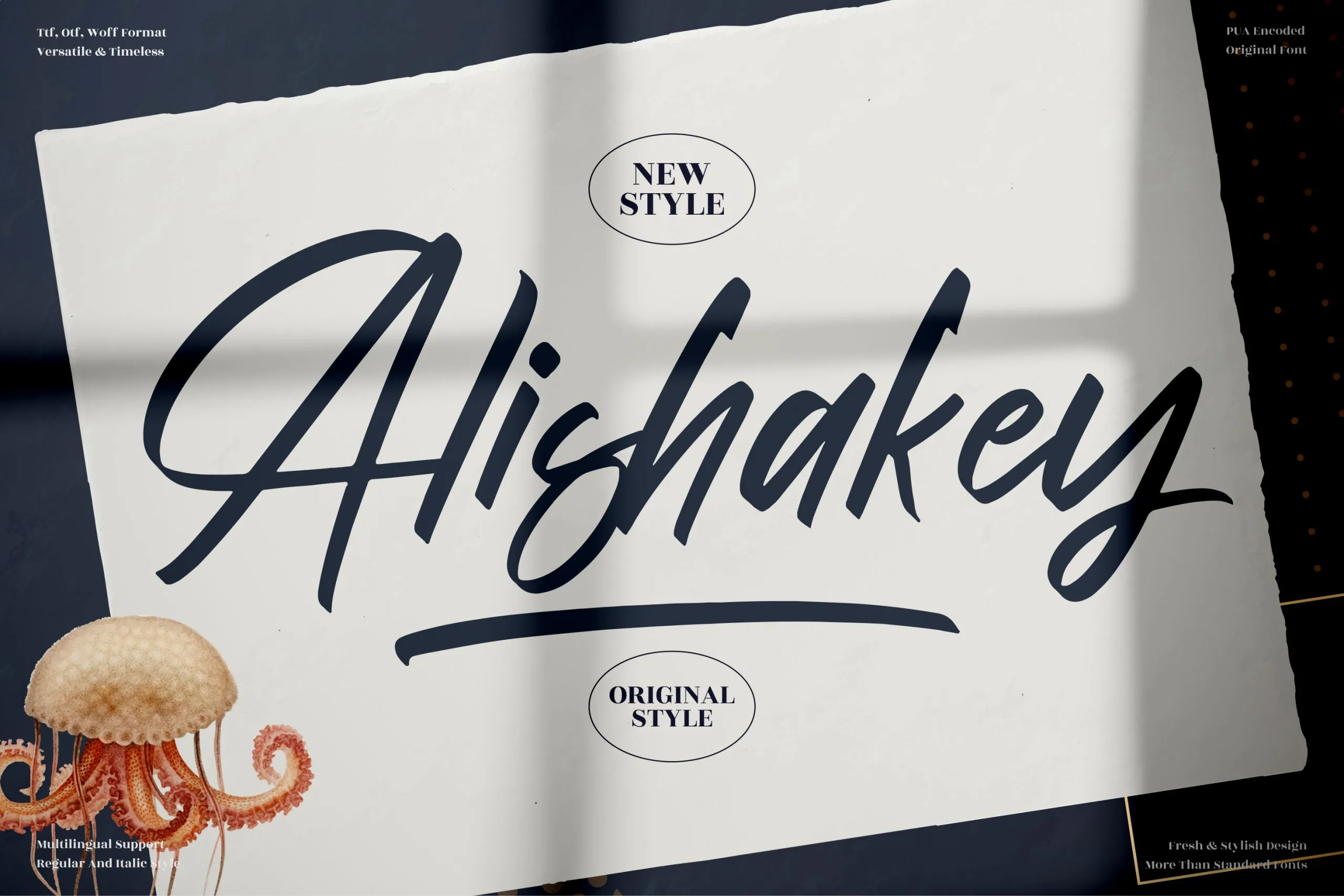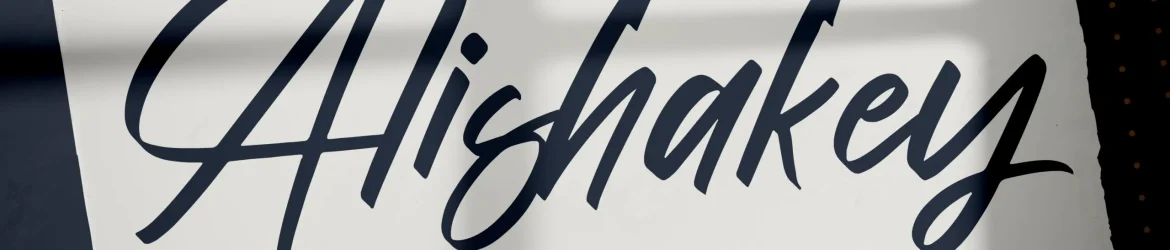
A Alishakey Font é uma elegante fonte escrita a mão que se destaca por seu charme natural, perfeita para projetos requintados. Embora não possamos replicar características específicas do designer perspectype, a fonte combina um sabor autêntico com detalhes finos e harmoniosamente equilibrados, adequando-se perfeitamente aos mais diversos tipos de aplicação. Com texturas variadas e uma variedade impressionante de caracteres, ela oferece flexibilidade para projetos que vão desde embalagens de produtos até arte digital, como logotipos, cartões de visita, e mesmo em materiais decorativos como mugs ou revestimentos de porta-folheto. Esta fonte é um ótimo complemento para qualquer projeto que busque uma sensação única e sofisticada, tornando-a perfeita para aqueles projetos onde a qualidade premium não pode ser dispensável. Alishakey é mais do que simplesmente uma ferramenta de escrita: ela transforma ideias em realidade, adicionando um toque especial ao seu design.